Font Terbaik untuk CV
Pemilihan font yang tepat untuk CV Anda memainkan peran kunci dalam menciptakan kesan pertama yang positif pada rekruter. Meskipun konten CV sangat penting, namun jangan abaikan juga pentingnya presentasi. Pemilihan font yang salah berisiko CV Anda akan terlewatkan, walaupun Anda memiliki keterampilan dan pengalaman yang relevan.
Isi CV seperti pengalaman dan keterampilan tetap menjadi penilaian utama rekruter, tetapi pemilihan font CV juga tidak kalah penting. Beberapa jenis font dianggap kurang profesional jika digunakan untuk dokumen lamaran kerja. Jika Anda tidak sengaja memakainya, bisa-bisa peluang lolos ke tahap interview bisa hilang begitu saja. Maka dari itu, ayo pelajari apa saja font yang direkomendasikan dan sebaiknya Anda hindari untuk membuat CV.
10 Font CV Terbaik yang Sering Digunakan
Memilih font formal untuk CV dengan desain klasik, simpel dan modern yang bisa digunakan oleh semua jenis sistem operasi merupakan pilihan yang paling tepat sekaligus aman. Font seperti Times New Roman, Arial, dan Calibri adalah pilihan terbaik untuk tampilan yang rapi dan profesional.
Berikut adalah rekomendasi font untuk CV profesional yang sering digunakan:
Font | What makes this font suitable for your CV? |
Arial | Arial adalah pilihan font yang rapi untuk digunakan dalam CV. Font ini adalah contoh font modern yang terbaik dalam hal keterbacaan yang mudah. |
Calibri | Jenis font yang satu ini dikenal sebagai pilihan andalan untuk CV. Bahkan, menurut Tren Rekrutmen 2025, 59% rekruter berpendapat memang lebih menyukai font klasik seperti Times New Roman atau Calibri di CV kandidat. |
Poppins | Poppins adalah font yang cocok untuk CV desain minimalis. Font ini tepat untuk Anda yang suka membuat CV dan surat lamaran kerja yang singkat tapi tetap gaya. |
Georgia | Untuk font yang klasik, Georgia adalah alternatif yang bagus selain Times New Roman. Dan karena font ini dirancang khusus untuk layar, rekruter tidak akan mengalami kesulitan dalam membaca. |
Times New Roman | Font ini banyak digunakan dalam dokumen profesional karena jelas dan mudah dibaca serta merupakan pilihan yang aman untuk sebagian besar industri. |
Trebuchet | Font CV ini termasuk klasik, tetapi tetap bergaya elegan dan cocok untuk profesi apa pun. Dari ukuran, font ini sedikit lebih besar daripada font lainnya. |
Lato | Lato adalah font modern yang berasal dari Google. Font ini berkesan profesional tapi tidak terlihat kaku. Cocok untuk industri yang inovatif. |
Garamond | Garamond adalah font serif yang menjadi pilihan terbaik untuk menampilkan kesan yang profesional dan elegan. Font ini adalah salah satu font yang disukai di industri konvensional. |
Noto Sans | Noto adalah font profesional untuk CV dengan desain yang simpel, open source dan tersedia secara gratis yang menjadikannya pilihan tepat untuk CV. |
Helvetica | Helvetica adalah font yang dikenal luas dan populer yang digunakan pada CV, terutama dalam industri desain. Font ini bersih, klasik, dan tak lekang oleh waktu. |
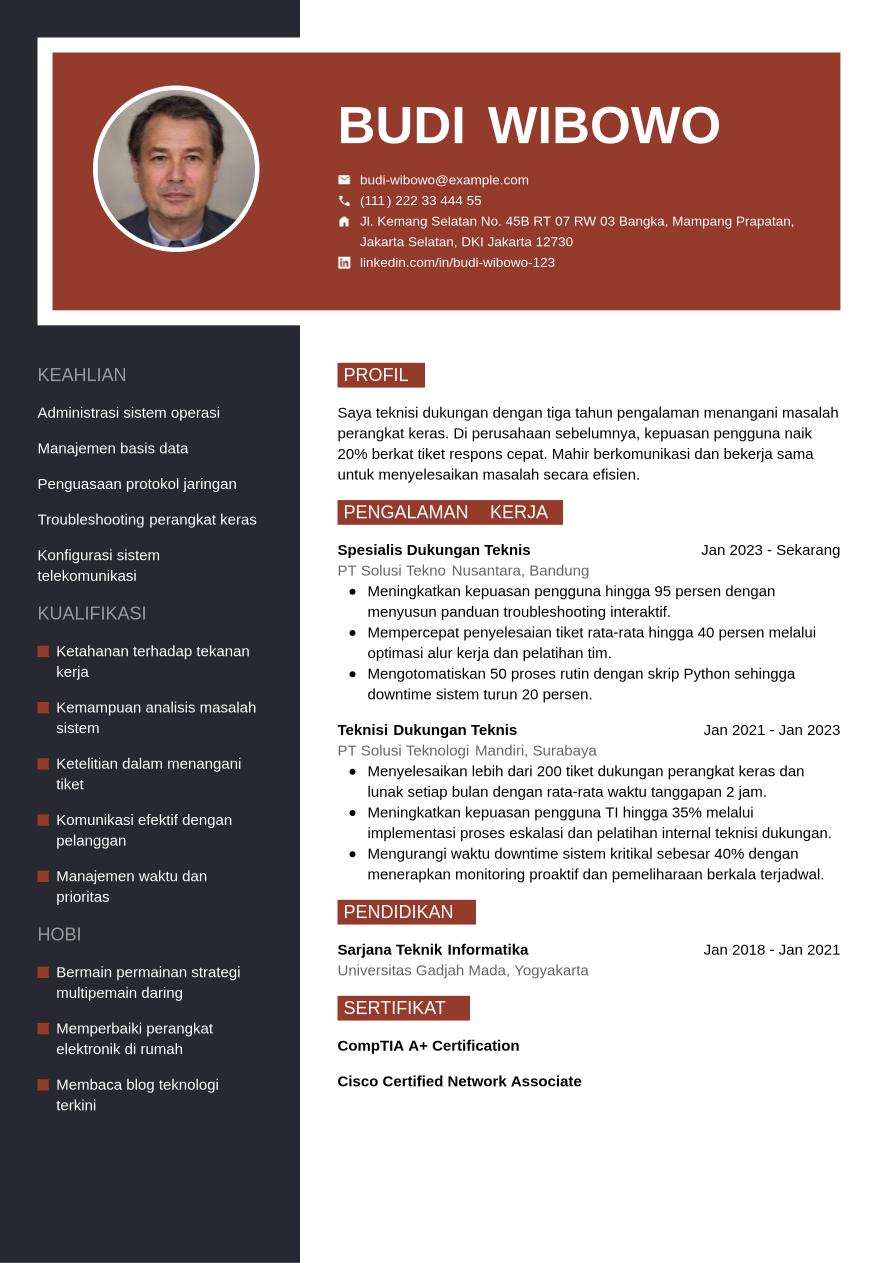
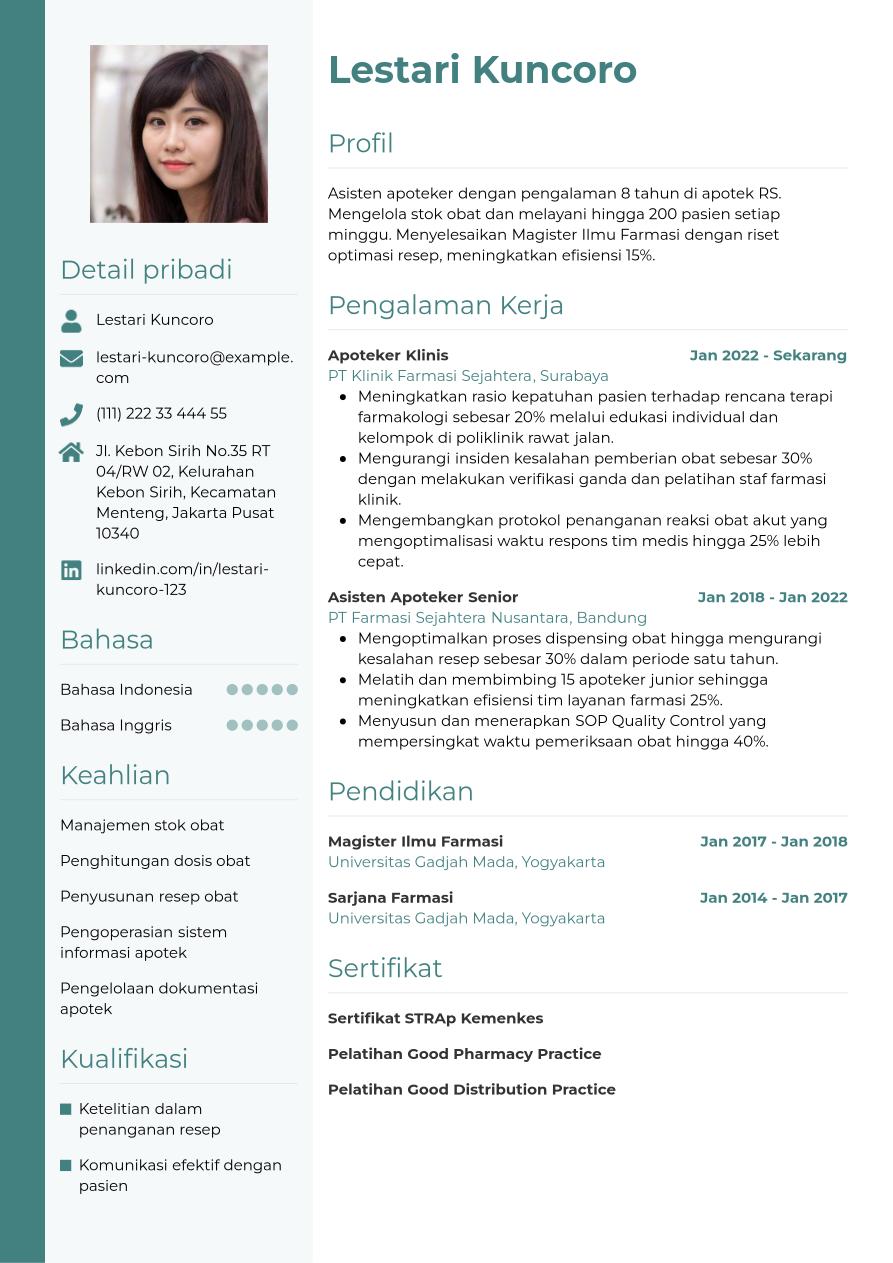
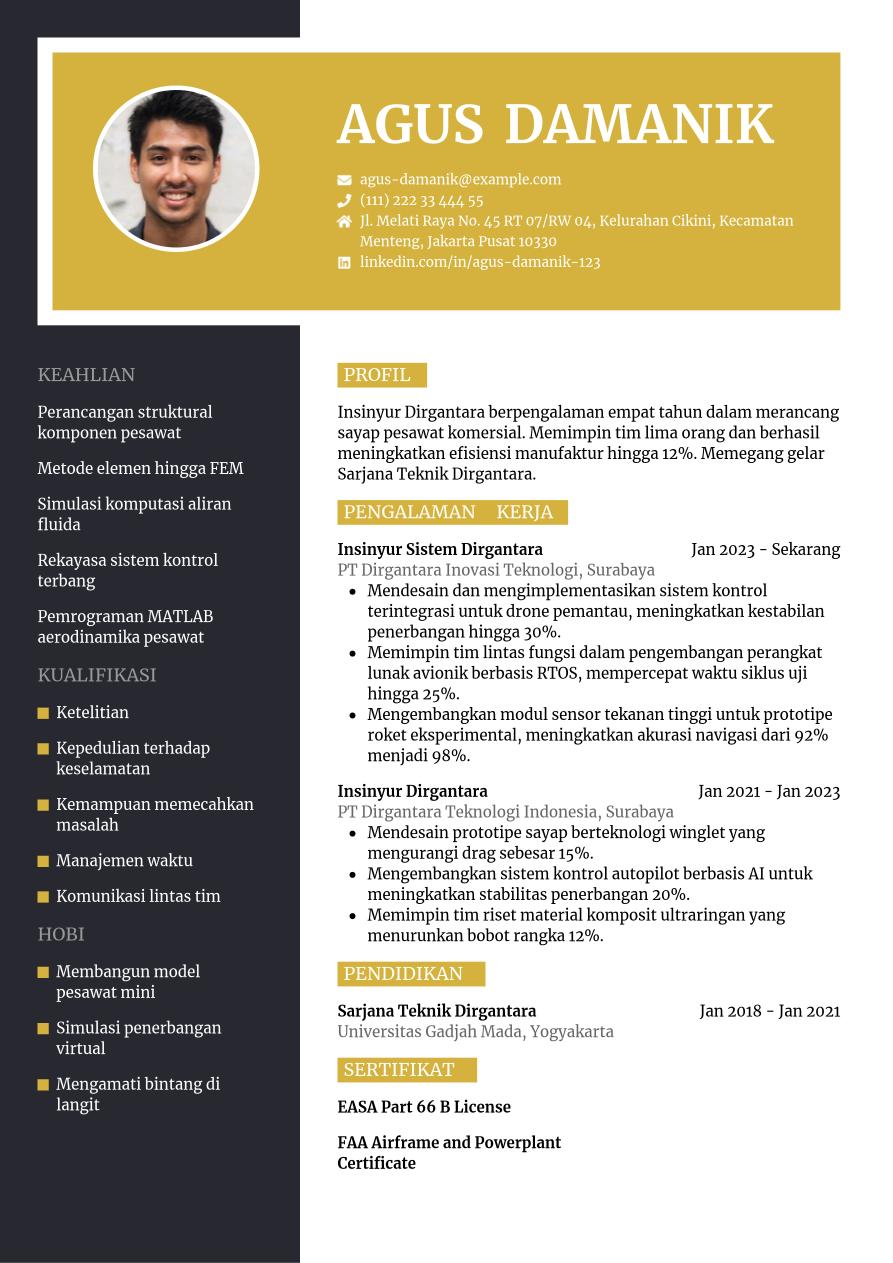
Font CV yang Harus Dihindari
Beberapa font CV di bawah ini perlu dihindari karena selain dapat membuat CV Anda sulit terbaca, akan menimbulkan kesan kurang profesional. Berikut beberapa di antaranya:
Font | Why should you avoid this font for your CV? |
Papyrus | Font ini terkesan sangat kuno dengan lekukan yang berlebihan dan dapat memengaruhi keterbacaan CV Anda. |
Comic Sans | Comic Sans adalah font yang terkesan tidak serius untuk CV. Font ini awalnya dirancang untuk komik, dan tidak pernah ditujukan untuk penggunaan profesional. |
Brush Script | Font yang berkesan seperti tulisan tangan ini terkesan kuno dan tidak mudah dibaca dari jarak jauh. |
Courier | Font seperti tulisan mesin ketik ini membuat CV Anda terkesan kuno, dan dipaksakan serta tidak profesional. |
Impact | Impact adalah jenis font yang tebal dan mencolok sehingga terkesan berlebihan dan sulit dibaca dalam ukuran kecil. Font ini lebih cocok digunakan untuk judul. |
Ukuran Font untuk CV Terbaik
Selain jenis font, ukuran font yang tepat untuk CV juga penting. Biasanya, ukuran font yang direkomendasikan untuk CV adalah antara 10 hingga 12 poin.
- 10 hingga 11 poin: Ukuran font CV yang lebih kecil seperti ini cocok untuk CV yang panjang atau dengan banyak informasi, karena memungkinkan Anda memasukkan lebih banyak teks dalam ruang yang terbatas. Font ukuran ini tetap mudah dibaca, tetapi rekruter mungkin perlu sedikit upaya lebih untuk membaca detailnya.